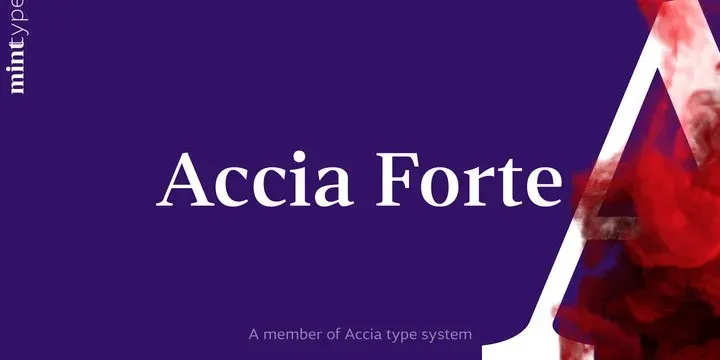
A Accia Forte Font é uma família serif romanesca que incorpora 8 estilos de traço, desde finos até preenchidos com muito detalhe. Suas linhas robustas e elegantes trazem um ar antigo ao seu design contemporâneo, o que a torna ideal para aplicações visuais variadas. Seja em títulos, cartazes ou sites web, essa fonte oferece um contraste atraente sem deixar de lado a delicadeza do estilo serifado. Com esse traço robusto e atemporal, a Accia Forte Font será uma escolha agradável para designers e criativos em busca de um traço versátil que se encaixa perfeitamente em seu trabalho visual.